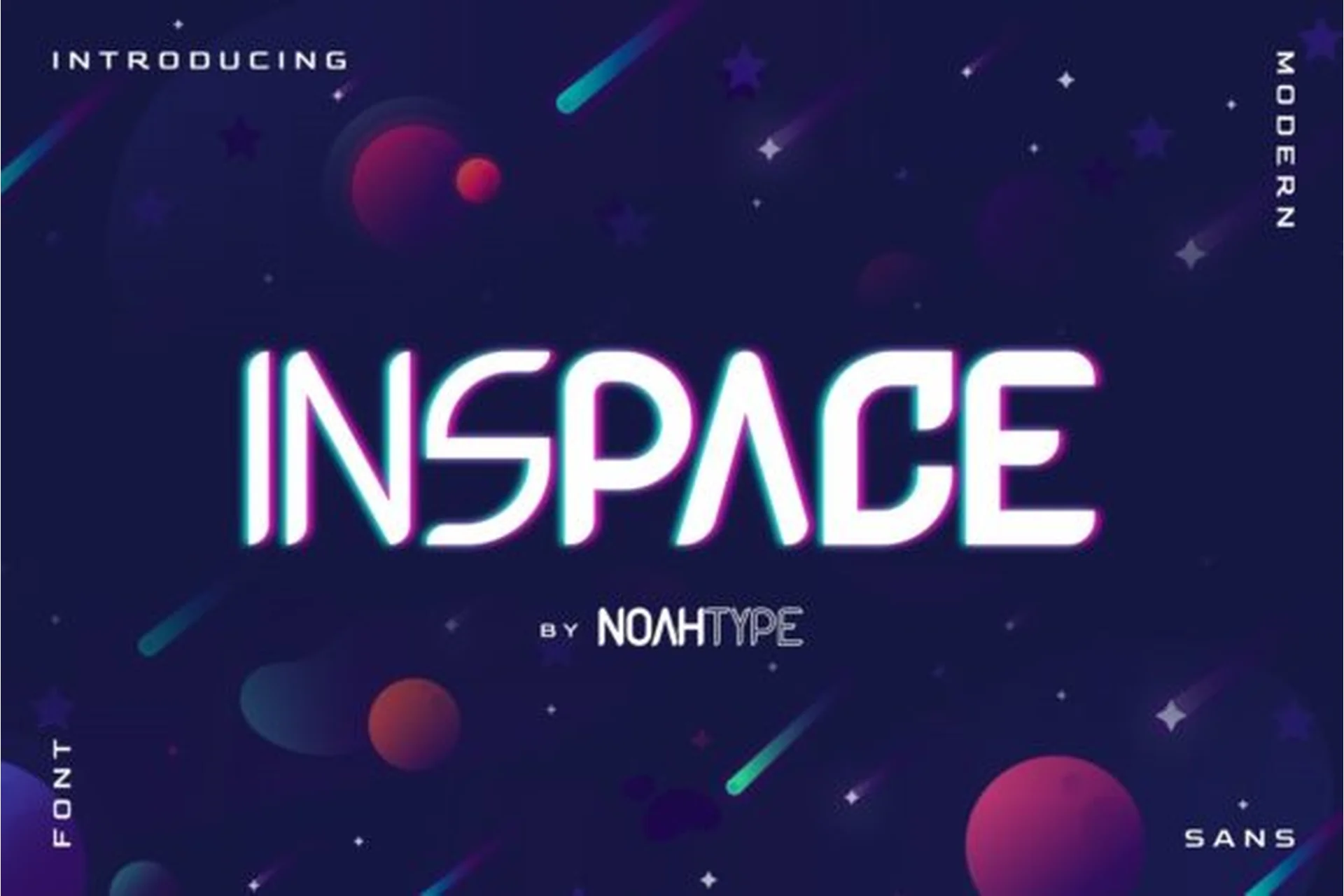
Inspace - футуристический современный дисплейный шрифт с уникальным стилем. Шрифт был вдохновлен аэрокосмическими технологиями, астронавтами, скоростью, компьютерными символами и плакатами о запуске. Он обладает уникальным стилем, который придаст особый эффект вашему дизайну. Этот шрифт отлично подходит для игр, технологических событий, заголовков, логотипов, плакатов, заголовков, продуктов и многого другого.